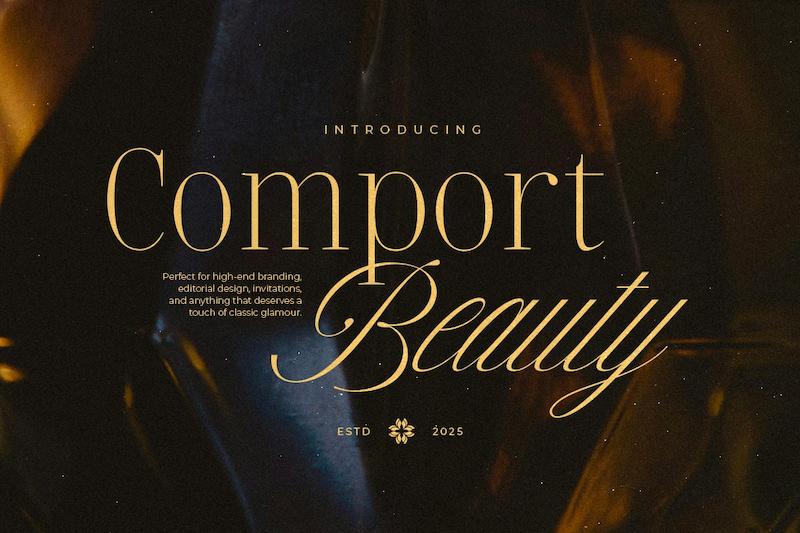
کامپورت بیوتی، یک فونت دوتایی عاشقانه و شیک است که زیبایی الگانت فونت سریف را به طرز چشمگیری با جذابیت دلنشین فونت اسکریپت در هم میآمیزد و هارمونی بینقصی را برای طرحهای رویایی شما به وجود میآورد.
این فونت برای کارتهای دعوت عروسی، برندسازی، طراحی لوگو، یا پروژههای با تم عاشقانه ایدهآل است و حس گرما و دلربایی را به تک تک جزئیات کار شما میآورد.
طبقهبندی: سریف، اسکریپت
فاصلهگذاری: نرمال
اندازه بهینه: هر اندازهای